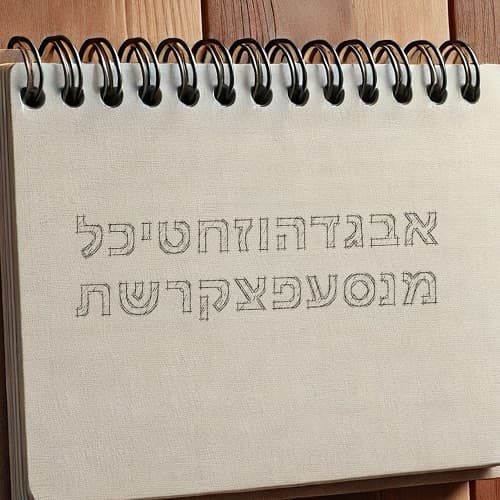
פונטים הם חלק בלתי נפרד מהעולם הדיגיטלי בו אנו חיים. זה לא משנה אם אנחנו עומדים לעצב אתר חדש, צריכים להכין מצגת לעבודה או כל דבר אחר – לבחירת הפונט המושלם יש חשיבות אדירה בכל הנוגע להעברת המסר שלנו.
במאמר הבא שאתם עומדים לקרוא, נסביר לכם כל מה שאתם צריכים לדעת לפני שאתם בוחרים את הפונט המושלם מבין מגוון פונטים פופולריים בעברית.
פונט, אותו נהוג לכנות בעברית גם בתור "גופן" הוא בעצם הסגנון בו מעוצבת צורת האותיות. בדרך כלל אנחנו פוגשים פונטים שונים היום בצורה דיגיטלית – תוכנת מחשב בה ניתן לרשום טקסט מסוים או לחילופין, באמצעות פלטפורמות נוספות בהן אנו משתמשים עבור הצגת מידע טקסטואלי.
ניתן להגיד כי עיצוב גופנים הוא תחום עצמאי של עיצוב גרפי לכל דבר, ואילו היום ניתן למצוא מגוון רחב של פונטים בעברית בהם ניתן להשתמש עבור כל מטרה.
כמובן שיש כמה פרמטרים שחשוב לקחת בחשבון לפני שנבחר את הפונט המושלם עבורינו מבין כל-כך הרבה אפשרויות שונות של פונטים פופולריים בעברית.
כאמור, היום ניתן למצוא מגוון רחב של פונטים פופולריים בעברית מהם נוכל לבחור. אולם, חשוב להדגיש כי לא נרצה לבחור סתם פונט אקראי – אלא יש חשיבות אדירה לפונט שנבחר עבור המסר שאנחנו רוצים להעביר.
ניתן להגיד כי הפונטים שאנחנו בוחרים עוזרים לנו לשדר מסר מבעד למילים עצמן, מסר חזותי שעוזר לנו להדגיש את תוכן המידע ואת הצורה בה אנו מעוניינים להעביר אותו לקרוא.
לצורך העניין, אם אנחנו כותבים מאמרים – בחירת הפונט יכולה לעזור לנו להדגיש כי את אופי המאמר.
בסופו של יום, נרצה לבחור פונט שונה לגמרי עבור כתיבת מאמר עם אופי קליל והומוריסטי מאשר מאמר שאמור להיות אינפורמטיבי ומיועד למשרד עורכי דין.
המדיה הדיגיטלית שינתה את חוקי המשחק בכל הנוגע לבחירת פונטים. נכון, גם לפני שנים רבות היו מספר פונטים פופולריים בעברית, אך הדפוס נכתב בעבר בדיו שמאוד מזכיר כתם בצורה בה הוא מתפשט, ואילו המדיה הדיגיטלית אותה אנו מכירים היום מורכבת בעיקר מפיקסלים.
הפיקסלים שכולנו מכירים, הם בעצם מעין נקודות זעירות שמרכיבות את המסך שלנו. בעבר הלא כל-כך רחוק, הסטנדרט המקובל היה שבכל אינץ' של מסך (כ-2.53 סנטימטרים) יש 72 פיקסלים, ובאיכות של הדפסה דיגיטלית יש 300 פיקסלים עבור כל אינץ'.
כמובן שהמסכים התקדמו מאז מאוד, וכיום צפיפות הפיקסלים גדולה הרבה יותר. ככל שצפיפות הפיקסלים תמשיך לעלות, כך פונטים לדפוס יהפכו יותר ויותר מתאימים למסכים לאורך זמן.
אולם, זהו מצב שונה לגמרי כאשר מדובר במדיה הדיגיטלית. בדיגיטל חשוב שהטקסט יהיה סנס-סריפי, כלומר טקסט ללא תגים בקצוות האותיות.
מעבר לכך, חשוב לא פחות גם שהטקסט לא יכיל קווים דקים מעבר לפיקסל אחד.
בהתאם לסטנדרט זה, נוצרה לאורך השנים מעין העדפה לבחירת פונטים מיוחדים בעברית שהקווים האופקיים שלהם זהים לקווים האנכיים בעובי – כמו פונט 'אלמוני'.
בחירת חבילת פונטים בעברית אינה עניין של מה בכך. כאמור, יש חשיבות אדירה מאחורי בחירת הפונט המושלם עבור השימושים הספציפיים שלנו.
הנה כמה טיפים שיוכלו לעזור לכם לבחור נכון:
הרבה יותר יעיל במקום זאת לבחור את הפונטים שלנו בהתאם ללקוחות הנוכחיים שלנו, כך שנוכל להתאים את הבחירה לעבודות הכתיבה הספציפיות שאנחנו עומדים לבצע בזמן הקרוב.
לשם כך, ניתן אף לחפש עבודות שנעשו בעבר על ידי שימוש בפונט מסוים, כך שנוכל לראות דוגמאות של שילובים מסוימים ובעצם כך נוכל לקבל השראה עבור השימושים העתידיים שלנו.
בדרך כלל, כאשר אנחנו בוחרים פונטים פופולריים בעברית פשוט מאוד למצוא עבודות הכוללות שימוש בהם.
כאשר נבחר פונטים בעברית להורדה, נרצה קודם כל להבין מהם ההבדלים ביניהם. להלן הסבר קצר על עיקרי הבדלי עיצוב האות בין סוגי פונטים שונים:
בדרך כלל, פונטים מיוחדים בעברית כוללים מספר משקלים כמו כבד, קל, בולד, רגיל וכדומה. כאשר נבחר פונט עבור טקסט רץ לצורך העניין, תמיד יהיה עדיף לבחור אחד עם שני משקלים – רגיל ומודגש.
משקל קל אינו מיועד עבור טקסט רץ ואינו מומלץ עבור שימושים כאלו, מאחר והוא אינו נוח לקריאה.
עם זאת, כאשר נבחר פונט עבור כותרת – משקל אחד בהחלט יכול לעשות את העבודה, אך גם כאן תמיד עדיף לבחור פונט מקצועי עם מספר משקלים על מנת לשדרג את עיצוב האתר שלנו.
לכן, כאשר נבחר את הפונט שנרצה לשלב מבין מגוון פונטים פופולריים בעברית – נרצה קודם כל לוודא כי משקל הפונט מתאים לשימושים שלנו.
כמוזכר לעיל, בעת בחירת פונטים פופולריים בעברית חשוב קודם לכן להכיר את סגנונות העיצוב השונים, ביניהם ניתן למנות סגנונות כמו כתב-יד, סריף, סנס, סלאב וכדומה. ובכן, חשוב להכיר את הסגנונות הללו בין היתר על מנת שנוכל להתאים אותם לאחר מכן לאופי של האתר שלנו.
לצורך העניין, אם העיצוב של האתר שלנו הוא בגווני הצבע האדם – בחירת פונט סריפי תתאים מאוד. לעומת זאת, אם בחרנו לעצב את האתר שלנו עם גוונים "קרים" יותר כמו כחול או אפור, עדיף לעבוד עם פונטים בסגנון סלאס.
כמובן שאם העיצוב של האתר שלנו ייחודי נוכל לשלב בין כמה סגנונות על מנת ליצור איזון – אך מוטב קודם לכן לוודא כי אלו סגנונות שמשתלבים היטב ביחד. כך לדוגמא, פונט סריפי יעבוד טוב לצד פונט סנס סריפי, בדיוק כפי שפונט מעוגל יעבוד טוב עם פונט ריבועי.
חשוב לוודא באותה הזדמנות כי לא בחרנו שני סגנונות דומיננטיים מדי, מאחר שבמצבים כאלו נוצר לנו מעין עומס ססגוני שעלול להשפיע לרעה על העיצוב של האתר שלנו.
בחירת הפונט המושלם היא חלק בלתי נפרד מעיצוב האתר שלנו, ולכן החלטנו להסביר לכם בכתבה זו כל מה שאתם צריכים לדעת לפני שתבחרו אילו פונטים תרצו לשלב באתר שלכם מבין כל-כך הרבה אפשרויות שונות של פונטים פופולריים בעברית.